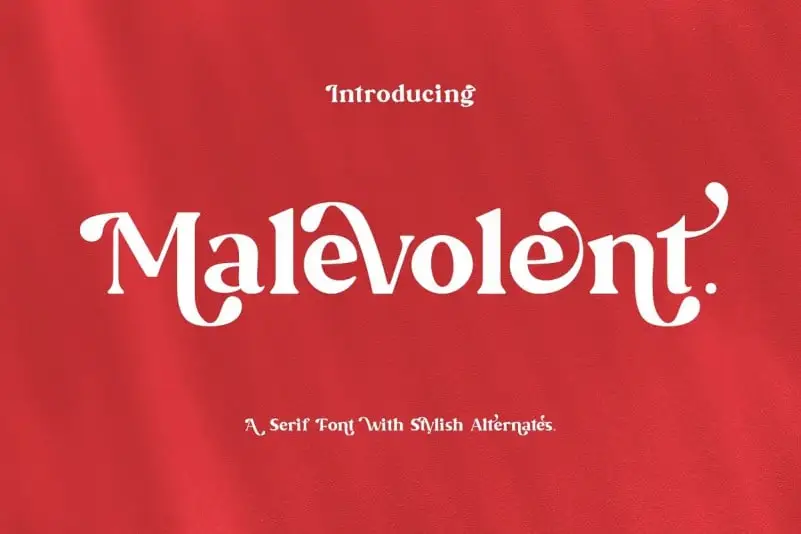
A Malevolent Serif Font é uma fonte serif vintage com alto contraste e acabamentos decorativos. Suas alternativas estilísticas e ligaturas criam um design único e distintivo, tornando-a perfeita para projetos de moda, como roupas ou acessórios. Ela também se adapta bem aos elementos que exigem um touch mais sofisticado, como assinaturas, capas de álbuns, logotipos, marcações, revistas e mídias sociais. A Malevolent Serif é uma opção versátil para qualquer projeto onde um toque acentuado de elegância seja desejado. É ideal tanto para aplicações fashion como para outros projetos em que você deseja destacar seu trabalho.